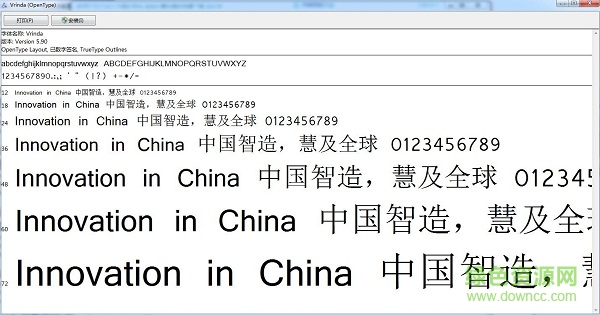
軟件介紹 軟件標簽: vrinda字體 英文字體 vrinda字體包匯聚了vrinda 黑體和vrinda常規(guī)體,該字體屬于無襯線字體,線條均勻流暢,體態(tài)大方,端正得體,可以用作正文排版也可用于大標題,有需要者歡迎免費下載!英文無襯線字體推薦nirmalaui bold字體 授權(quán):免費軟件 WinAll, WinXP, Win7大?。?60KB語言:中文nirmalaui是什么字體?nirmalaui字體是一款多用于平面設(shè)計的無襯線字體,本站提供的免費字體包收錄了nirmalauibold和nirmalauiregular字體兩款,需要的朋友快來下載吧!英文字體字號介紹1.英文字號大小習慣以point下載地址adele light字體 授權(quán):免費軟件 WinAll, WinXP, Win7大?。?.2M語言:中文adelelight字體是一款時尚纖細的英文字體,該字體豎線長,線條極細,結(jié)構(gòu)新穎,華麗柔美,多用于化妝品廣告、雜志、時尚期刊等領(lǐng)域,喜歡的朋友快來下載吧!gbk字庫介紹GBK編碼,是在GB2312-80標準基礎(chǔ)上的內(nèi)碼擴展下載地址無襯線字體特點sans-serif字體在字符筆畫末端沒有任何細節(jié)。與serif字體相比,它們的外形更簡單。Arial和Verdana就屬于sans-serif字體。vrinda字體安裝說明1.針對win7系統(tǒng),用戶只需選中字體右鍵安裝即可2.控制面板/字體/文件/安裝新字體3.安裝多款字體,可直接將字體復制到C:\WINDOWS\Fonts 軟件截圖 上一張下一張(1 / 1) 安裝詳細截圖 猜你喜歡 斜體字體 斜體字體 斜體字體,獨特的傾斜角度加上多元化的用途帶來不一樣的字體視覺效果,實用性高用途廣泛十分值得一試。需要的朋友趕緊來下載吧! 查看更多>> 黑體斜體 2.92M/中文/2.8/下載 vrinda 黑體/斜體 2.44M/中文/5.0/下載 nueva std-常規(guī)斜體 2.44M/中文/6.6/下載 digiface常規(guī)斜體 34KB/中文/6.6/下載 batang-粗體(韓文)/常規(guī)斜體 6.64M/中文/1.4/下載 宋體斜體字體 2.44M/中文/1.2/下載 其他版本下載 標題 大小 更新日期 下載 下載地址 電腦版 vrinda 黑體/斜體 點擊報錯 軟件無法下載或下載后無法使用,請點擊報錯,謝謝! 關(guān)閉報錯反饋 請描述您所遇到的錯誤,我們將盡快予以修正,謝謝! *必填項,請輸入內(nèi)容 本類最新 sounso beauty字體 spyced哥特英文字體 ttf版 zerodegrees字體 the next font ttf版 coolvetica font keep calm ttf 免費版 相關(guān)文章 Linux 防火墻配置基礎(chǔ)篇 新手如何遠程管理windows2003服務器 Linux下FTP的配置與應用 LINUX下MYSQL完全安裝使用指南 linux網(wǎng)站建立步驟 Sendmail 554 錯誤的解決 用戶評論 熱門評論 最新評論 發(fā)表評論 查看所有評論(0) 昵稱: 請不要評論無意義或臟話,我們所有評論會有人工審核. 字數(shù): 0/500 (您的評論需要經(jīng)過審核才能顯示)